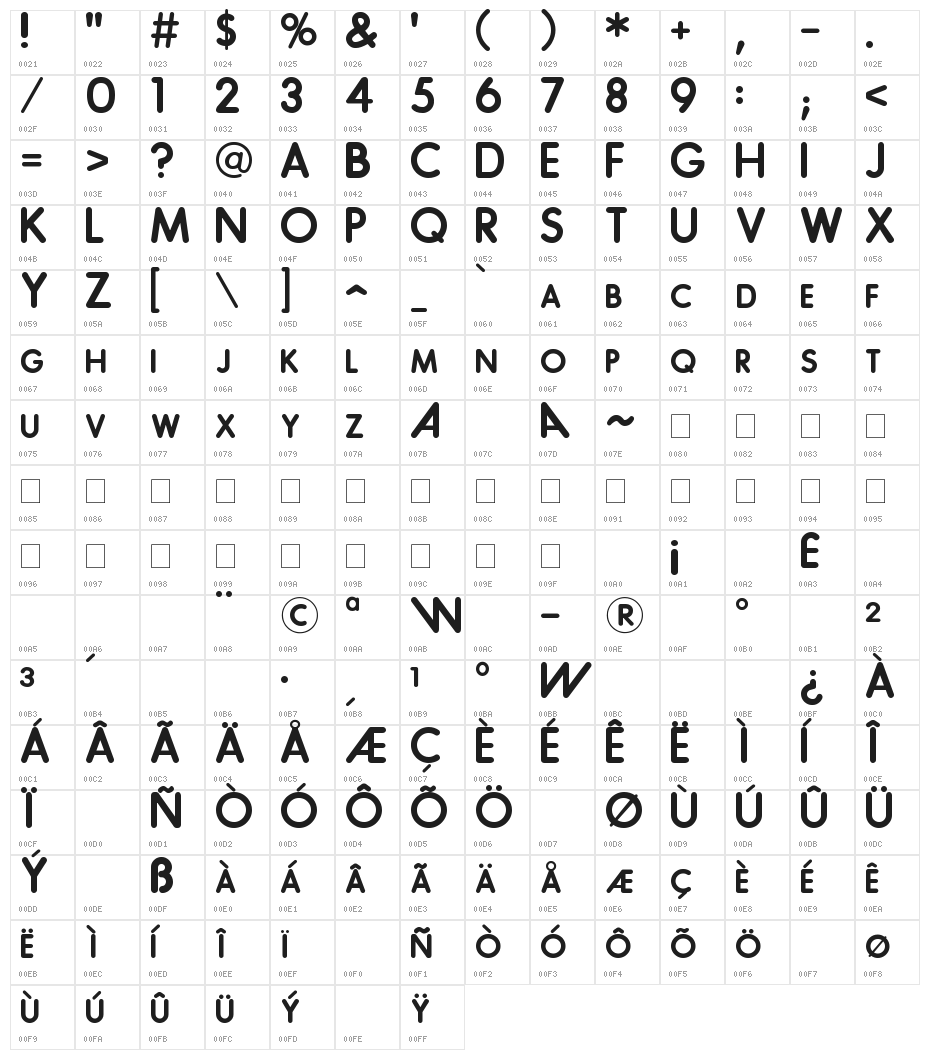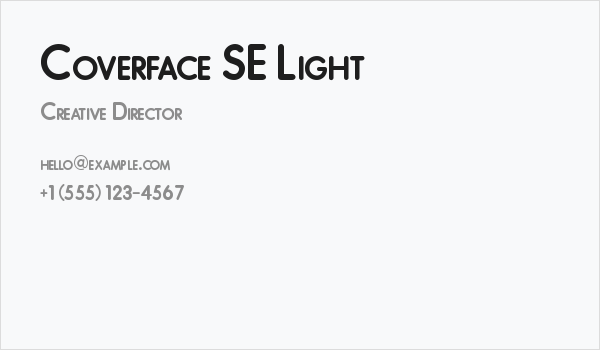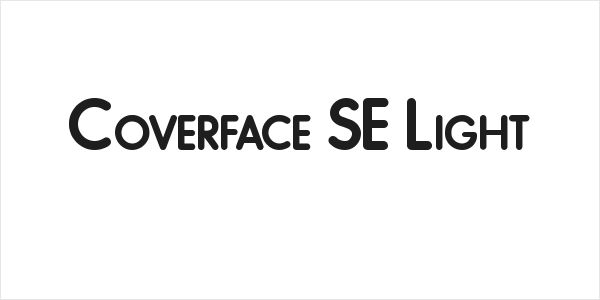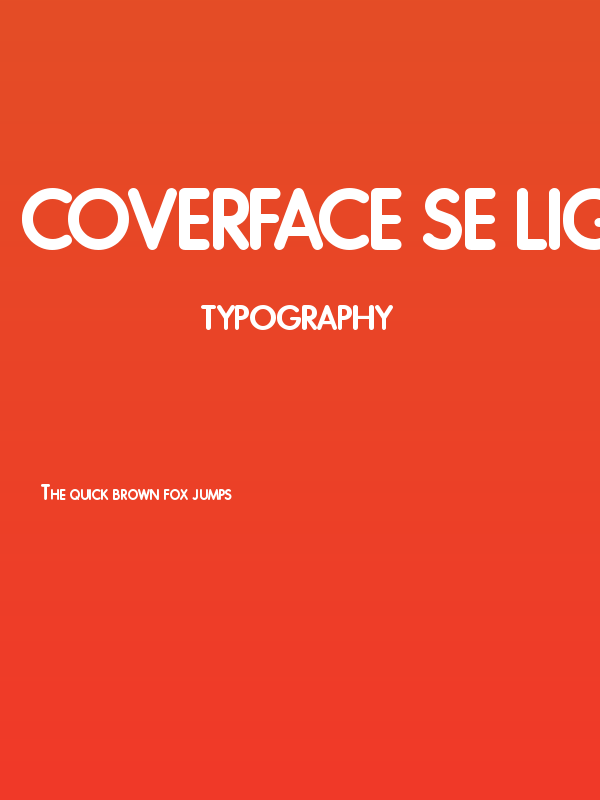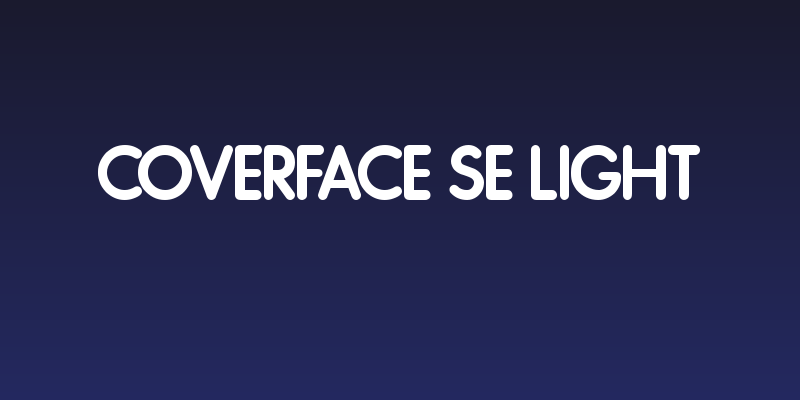
Coverface SE Light Font
| Caso d'uso | Headlines, Logos, Branding |
| Progetti proposti | Ideal for branding, advertising, packaging, and children's books due to its friendly and approachable style. |